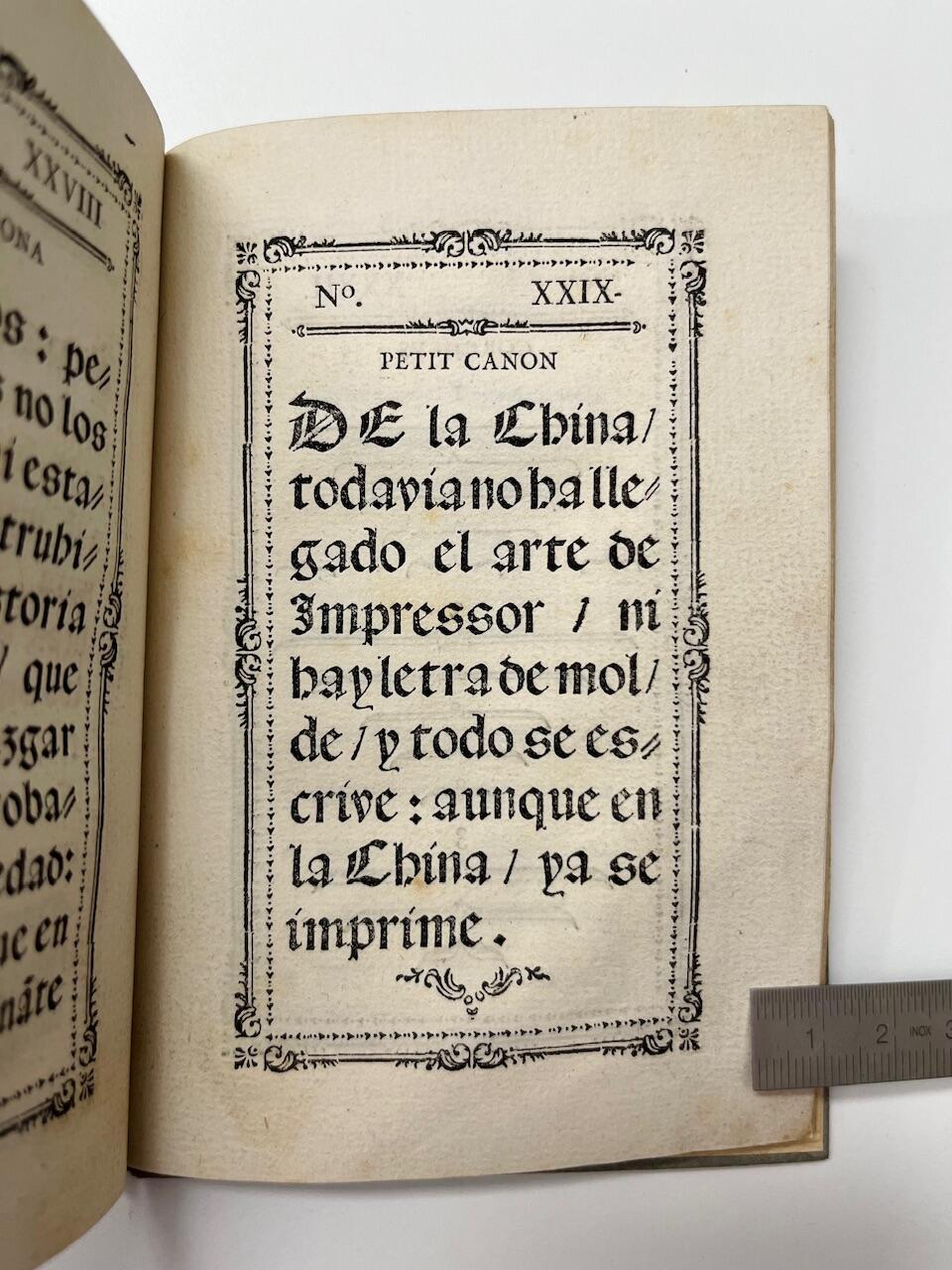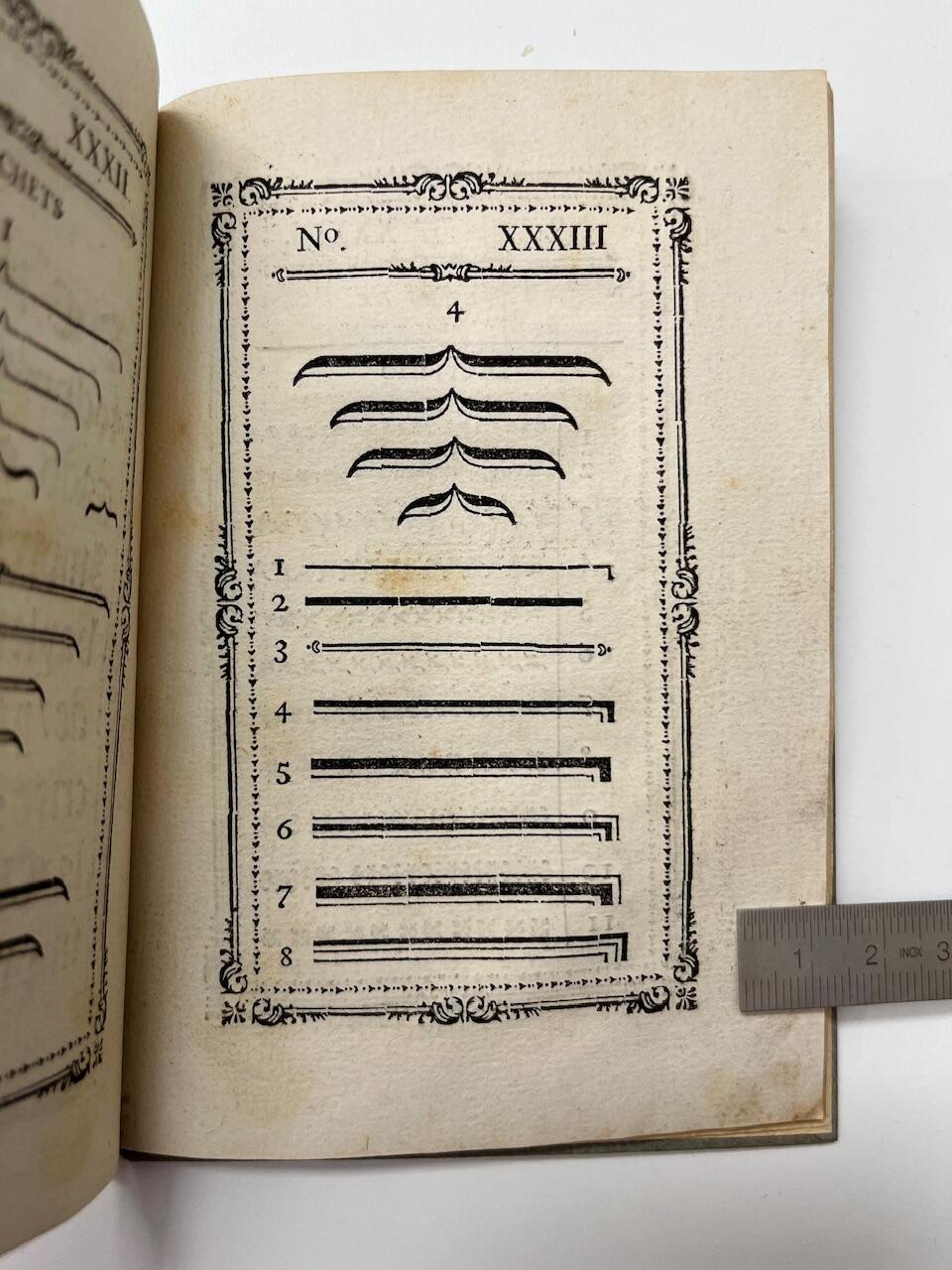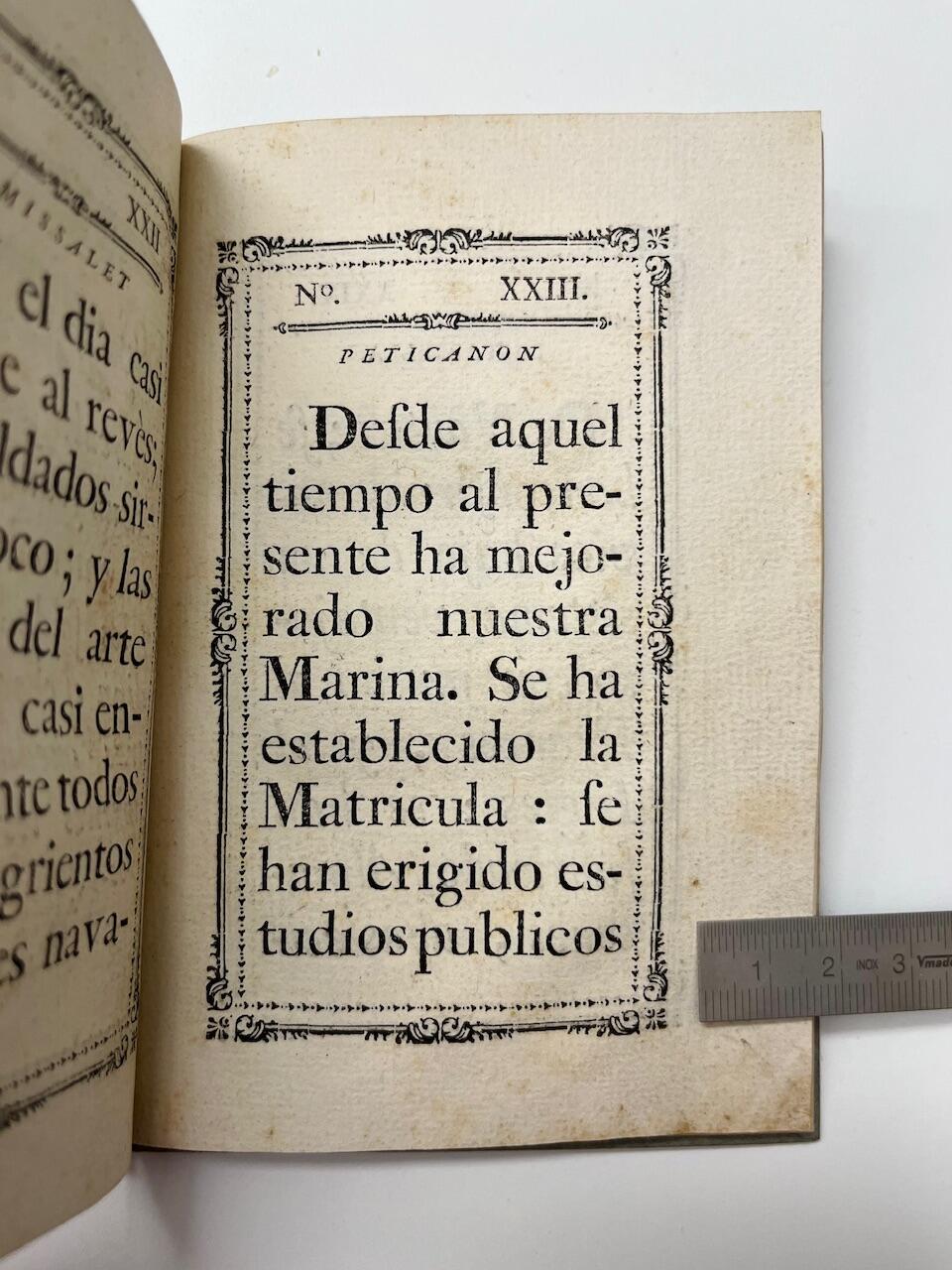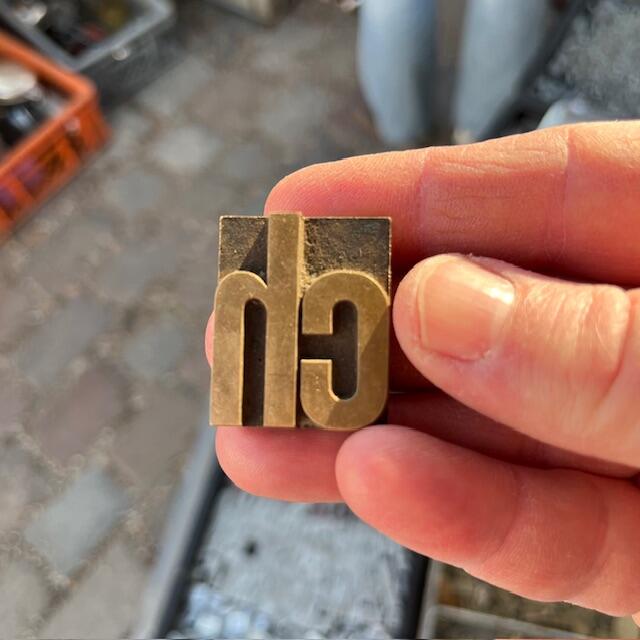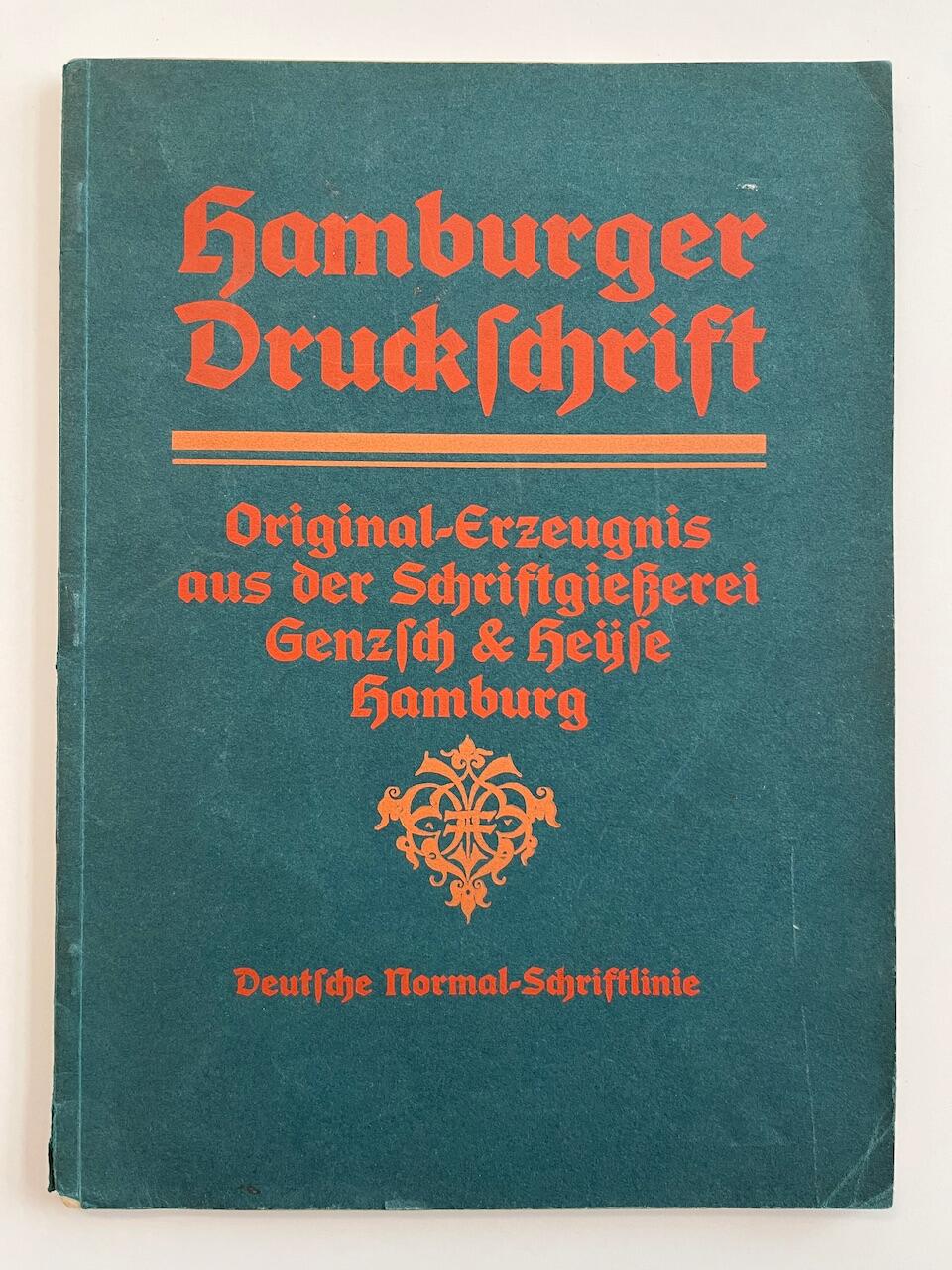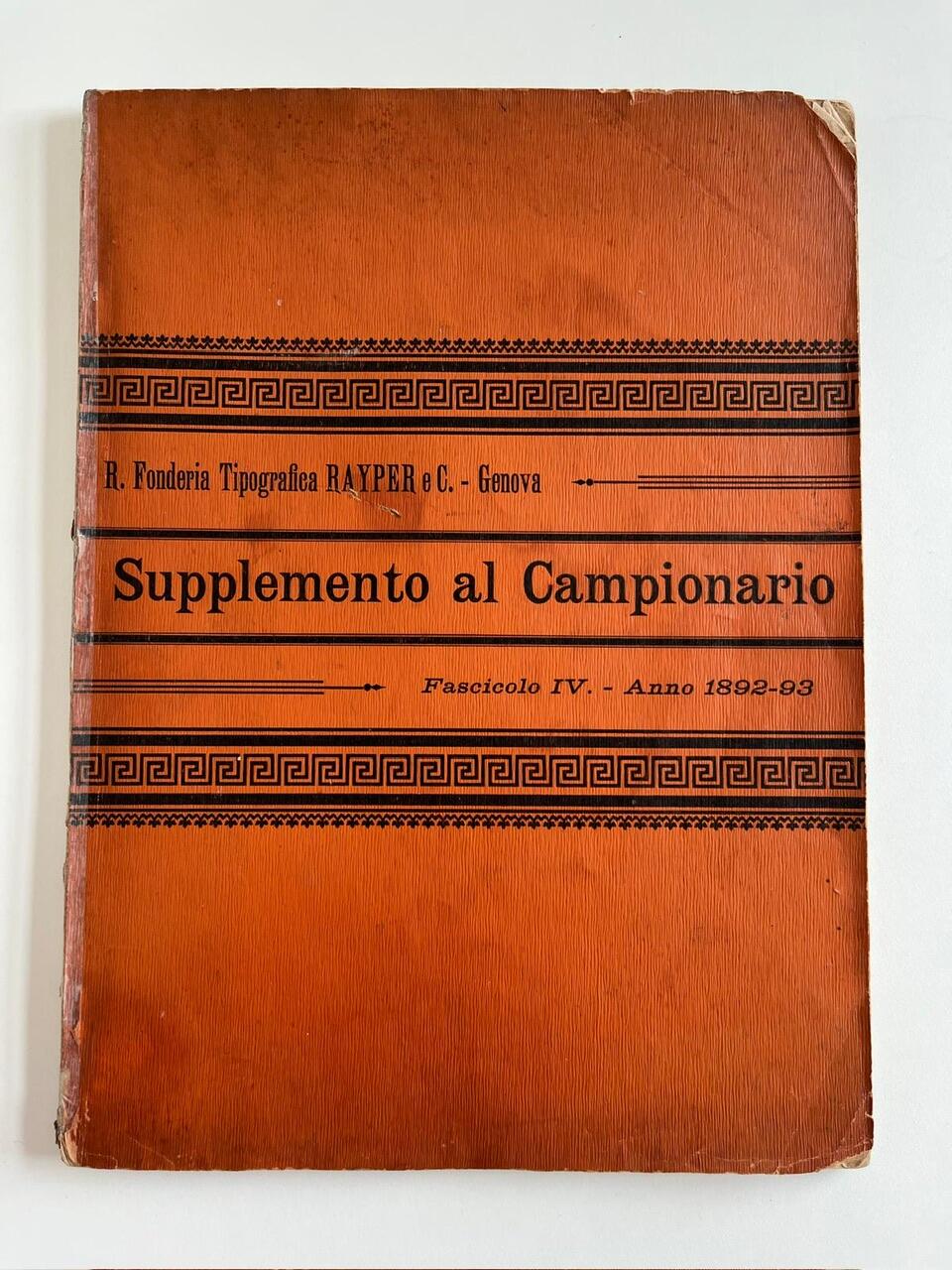
Wirklich gut passen die beiden Ligaturen in der Kombination für mich nicht … Einzel sind sie besser eingebunden. -?
Meine Verwandten heißen Verweyst und haben holländische Vorfahren, da steht das y halt für ij. Vielleicht haben die Heyses ähnlich gedacht?
Aus Bleisatzzeiten?
Compugraphic hat Fotosatzsysteme hergestellt. Die Dose dürfte aus den 1970ern oder 1980ern sein …
Es tauchen immer noch Muster von Gießereien auf von denen ich noch nie gehört habe … shock
Versteht jemand die hochgestellten T und S? Ich nicht.
Das ist die Begründung:
The elevated ‘S’ and ‘T’ are a subtle nod to the building’s history, and are inspired by typographic details found in a book in the Cathedral’s Library. This unique detail reflects St Paul’s heritage while embodying its spirit of transformation and welcome.
Antwort ja schon mitgeliefert
Abgesehen davon, hat mich das gleich entfernt an so Steinmetz-Kürzel erinnert … ich fand’s einfach optisch-emotional stimmig, ohne viel drüber nachzudenken.
Um es noch deutlicher abzugrenzen: Compugraphic hatte nie was mit Bleisatz zu tun, weder Maschinensatz noch Handsatz. Aber dafür die ganze Linotype-Bibliothek geklaut und unter anderen Namen vermarktet. Compugraphic startete mit dem opto-mechanischen Fotosatz, gefolgt von diverse Generationen digitalen Fotosatz. Compugraphic wurde irgendwann zu AGFA-Compugraphic und kaufte unter anderem Monotype (nicht andersrum).
Ich versteh deine Frage nicht, da du die Antwort ja schon mitgeliefert hast … ?
Du meinst die Begründung von Pentagram? Hmmm … überzeugt die Dich?
Und ich eben so rein gar nicht. 😬😭
… überzeugt die Dich?
Durchaus. Nicht nur, dass diese Schreibweise bereits in einem (vermutlich sehr alten) Buch bereits genutzt wurde, sie umgehen damit auch das unschöne »ST.« im Versalsatz und den notwendigen Apostrophen.
Ihre »Referenzen« haben eine andere Logik. Wenn es so umgesetzt wäre wie da (nämlich alles innerhalb der Versalhöhe), würde ich wohl weniger stolpern, zumal sie es im davon abgeleiteten Font auch anders machen:
Die beiden Bilder sind nicht ihre Referenzen. Das obere ist Teil der Monumente in der Krypta der St Paul’s Cathedral in London, das ist eine fest installierte Marmorinschrift. Die Referenz bezog sich aber doch auf ein Buch in der Bibliothek von St. Paul.
Und ich eben so rein gar nicht.
Genau, wir reden hier dann wohl über Geschmack und nicht über »Regeln«. Kann ich mit leben …
Die Referenz bezog sich aber doch auf ein Buch in der Bibliothek von St. Paul.
Stimmt. Wohl darauf hier (Sekunde 5):